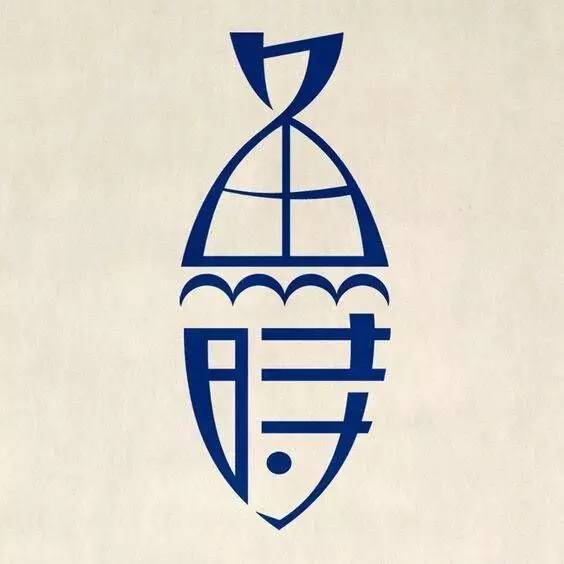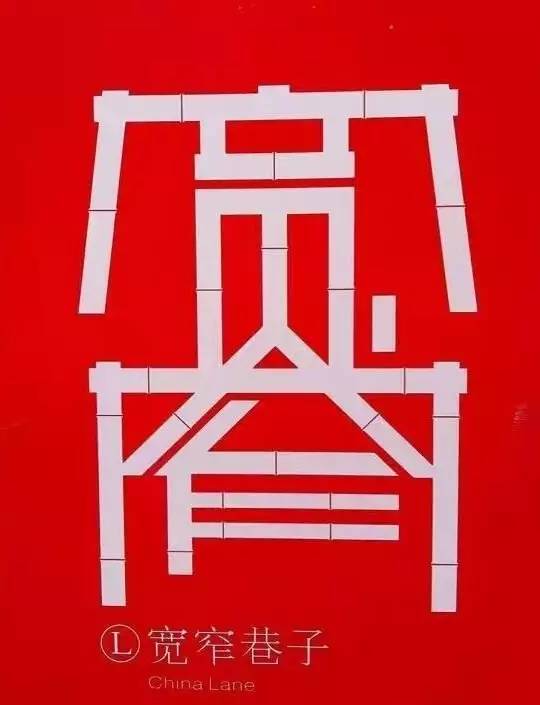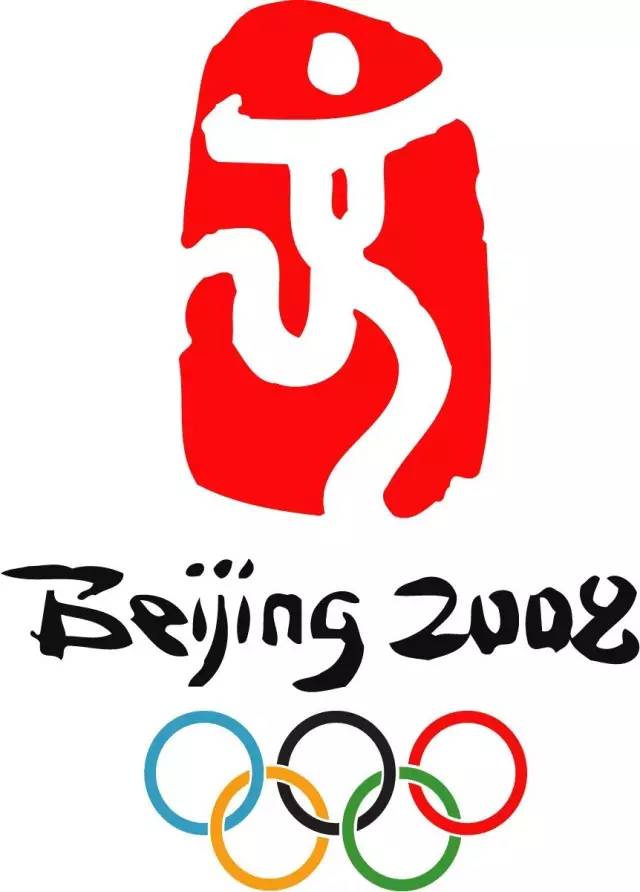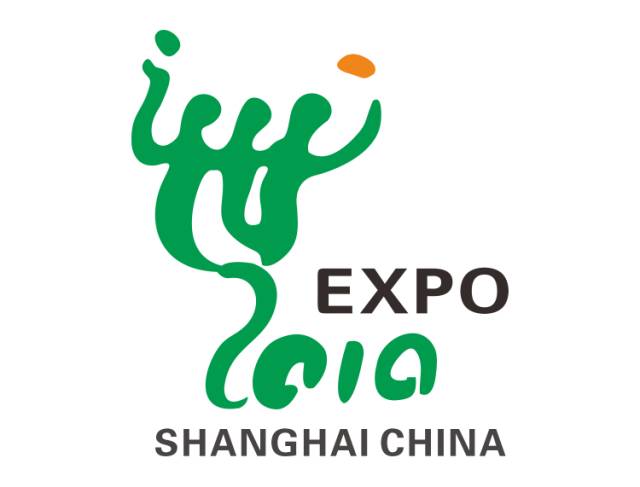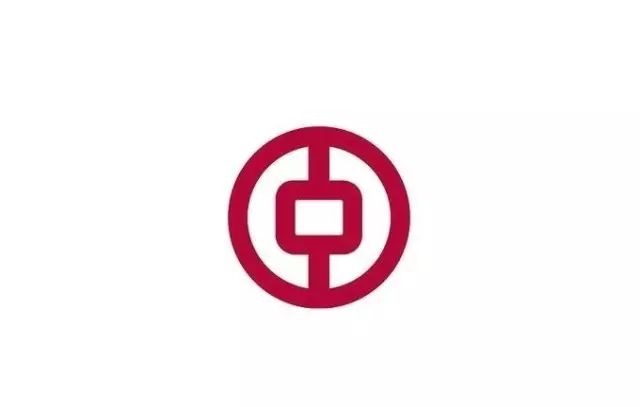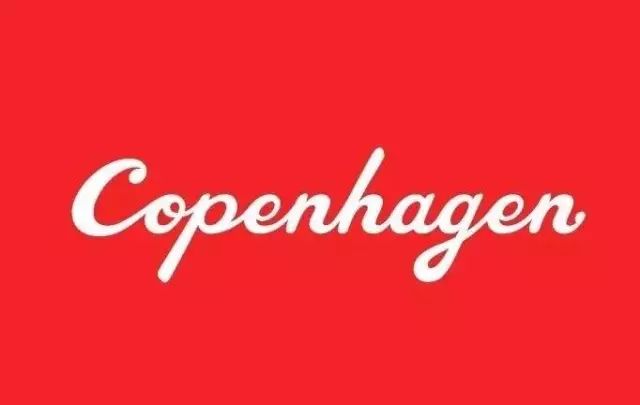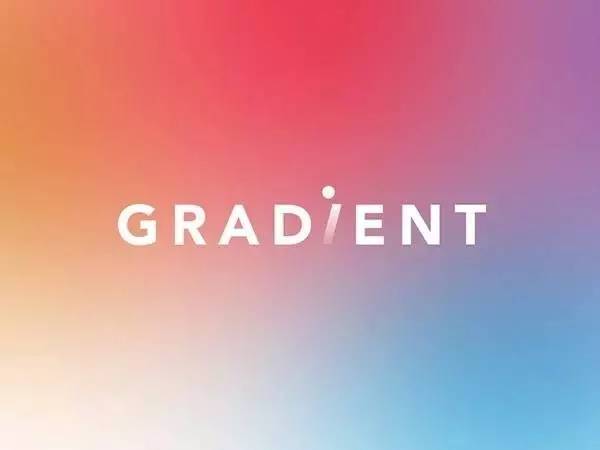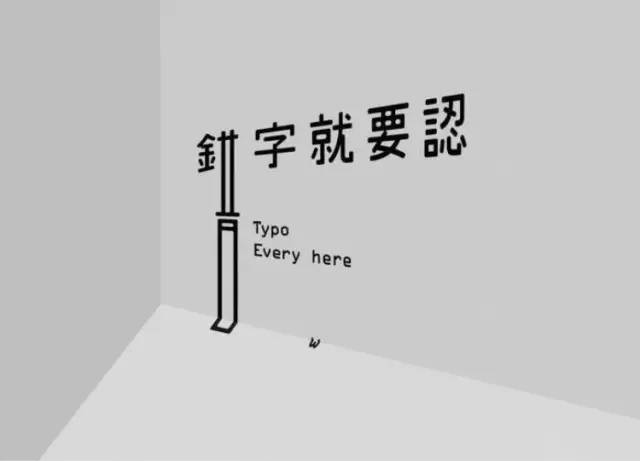
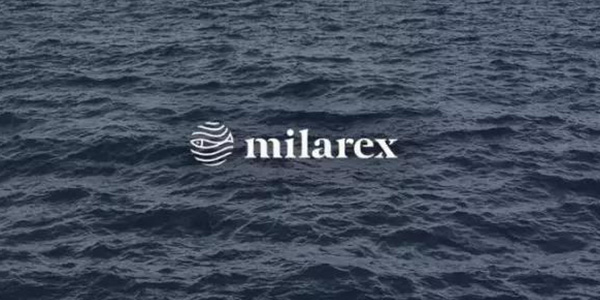
Logo字体设计的神奇效果是什么?
文字是人类沟通的重要载体。在设计领域,文字早已成为视觉传达的媒介之一。Logo字体设计以其简单、美观、概括性高等特点,受到了许多品牌的青睐。
字体设计的概念
字体设计是为了达到某种特殊的需要,经设计者深入分析品牌特点后,再融入企划者的思想情感所设计出的字体。Logo是Logotype一词的缩写,它指的是一个完整的、不可分割的,且具有造型性、统一性及识别性的字体设计。
在古希腊时期,“Logo”的含义除了“字”的意思,它还有“宇宙”的含义。从释义上即可看出,当时Logo的基本要求除了是有形的字以外,还必须具备完整性。
近些年来,Logo的定义更加广泛,不再单纯以文字作为表现形式。只要是具备固定形态和统一性的整体就都能被称为“Logo”。
在设计领域,字体是视觉传达和信息传达的重要媒介之一。如何运用好文字,充分利用其效能呢?其中,重要的是要去理解文字,才能做出最贴切的设计作品。
字体设计的重要性
字体设计随着社会的发展一同进步,它是人类文明演变的见证者。无论是具有形意功能的汉字,还是具有几何化特征的拉丁字母,它们都以简洁、独特的性质吸引着人们的眼球。
字体设计广泛地应用于各种领域当中,例如招贴设计、书籍设计、标志设计以及包装设计等等。
文字的主要功能是通过视觉向大众传达一些信息和意图,因此,准确性是文字表达的一大特点。尤其是在商品广告的设计上,一个标题或一个标志就能将商品的内涵准确无误地传达给消费者。
文字虽然看起来简单,但是在字体设计上却有着无限可能。只要从字的形态与编排上不断创新,就能给人带来不一样的视觉效果——或是端庄秀丽,或是欢快轻盈,又或是新颖独特。
在视觉传达的过程中,文字作为整体画面的要素之一,具有传达情感的功能。好的字体设计不仅关注局部,而且对结构、字形及整个设计都有全盘把握。一次巧妙的字体设计会令人感到愉快,甚至对背后的品牌产生好感。
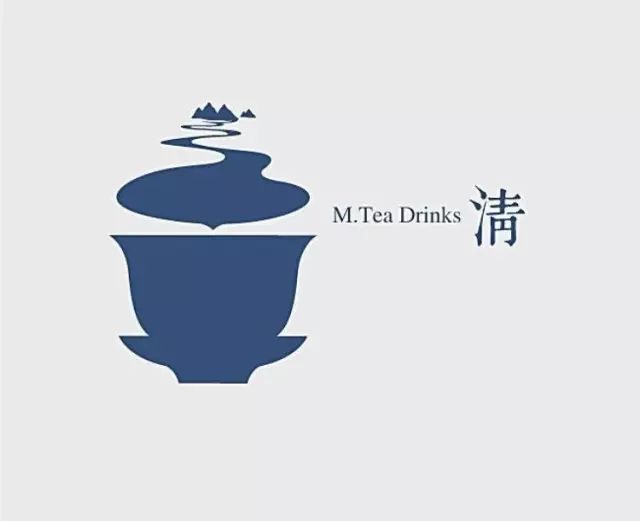
创意字体设计最大的特征是其具有装饰性。自古以来,汉字都因其独特的装饰美被用在鼎、钟、印等器物上,也被用于装饰瓷器、刺绣等工艺品。如今,创意使文字拥有了新的生命力,吸引了更多人关注的目光。
Logo字体设计对品牌的影响
Logo是联系品牌与消费者的中介之一,一个知名的品牌可以通过其知名度来扩大其标志的识别度。同样地,一个好的标志也有助于品牌获得更大的成功。
2003年4月,联想将其原有标志“LEGEND”换成“Lenovo”的主要原因是联想在准备进入海外市场的时候发现,原有的标志在多个国家已被注册。
联想为了开启自己的国际化战略,不惜花重金获得了2004年奥运会赞助商的资格,并借助这个世界性平台将自己的Logo与奥运五环连在一起,为品牌创造了更多的曝光机会。
诺基亚(NOKIA)最早是一家在芬兰Nokia小镇附近的造纸公司,它最初的标志是一条长相怪异的鱼。尽管公司早在上世纪初就进入了通信行业,但是他们依旧沿用了这个标志,直到上世纪60年代。这就导致有些人在看到这个标志时,以为这是一家有趣的饭店。
2010年10月,美国服装品牌Gap在其官网发布了新商标,一改品牌使用了20年的蓝底白字标识。不久以后,社交网络上充斥着对Gap新商标的吐槽,大量顾客宣称不会再购买此品牌商品。10月11日,Gap最终决定撤回新标,沿用之前的经典Logo。
时尚界有众多高端大气的奢侈品牌,它们作为全球时尚界的风向标,其品牌的标志也成为了独一无二的经典。例如香奈儿高雅简洁的标志、芬迪品牌的双F标志、圣罗兰富有节奏性的标志等等。
标志字体设计可谓是最富有创意的工作之一,它在方寸之间浓缩了大量的信息,通过文字表达出了不同企业的文化及风格。正如美国广告专家约翰·菲利普·琼斯所说:“品牌由品牌标志的发展而来”。
汉字在Logo设计中的运用
汉字以其独有的民族性成为了中国的标志之一。汉字字体的多样性大大地丰富了标志设计的表现形式,为设计师开拓了更为广阔的创意空间。
在中国古代,汉字早已作为设计元素出现过。它从最原始的基本形状,发展到当今富有创意且含义深刻的标志符号。目前汉字标志设计的应用在我国很普遍,也十分具有代表性。
2008年,北京奥运会的会徽采用了汉字中的“京”字,完美地将中国传统文化元素与运动的人物形象相结合,形象地表现出了富有中国特色的奥运精神及人文情怀。2010年,上海世博会标志以“世”字为主体架构,采用了中国书法率性的表现手段,巧妙地将传统文字与时尚理念相结合,成为了汉字标志设计的典范之一。
由于汉字自身具有形式美感,因此在许多标志设计中都有借汉字的外形表达含义的案例。例如中国银行的标志借用古代铜钱的造型特征,将外部形状与汉字“中”相连接,造型简练、含义突出;上海永久牌自行车的标志利用“永久”二字,组合成了一个自行车的造型。
中国银行Logo
以汉字作为标志的最大特点,就是以最简洁的方式把事情表达得简单易懂,让人看过标志以后就能理解其中的含义。
Logo字体设计的发展趋势
如今,我们可以利用电脑和数字技术使所有形式的字体都成为可能。经济的发展和品牌之间激烈的竞争推动了新的字体样式不断诞生,字体设计正向着多元化的方向发展。
简洁是现代标志字体设计的主流风格。无论是字体设计还是字体排列,现在的设计者都偏爱使用极简风格的造型,使Logo更加突出。
图形化是文字起源时的状态,由象形发展到象意是一个漫长的进化过程。现在许多Logo中的字体都图形化到了极致,这使字体的信息承载功能变得更加强大。
无论是中国的传统艺术还是西方的涂鸦,都足以证明很多设计师在思考字体的设计过程中费了很多心思。在现代标志字体设计中,装饰字体已有了更广泛的含义,它可以通过多元化的装饰手法来表达,例如材质、油漆、灯饰、马赛克褶皱带等等。
当下,字体可以绘制成三维的视觉效果,如平视、投影等多种效果的立体字。这种效果被广泛运用到网页的Logo设计上,它具有对比鲜明、视觉冲击力强等特点。
材质字体是一种利用各种材料的肌理效果,实现字体创意的设计手法,有缠绕、拼贴、排列组合等视觉字体技术。有些材质字体是由计算机制作而成的,有些材质字体则是将摄影收集的素材转化成图形材料。
设计是一种国际化的语言,它不但有利于文化的交流,也使各个民族的特色有了展示的平台。随着经济的发展和科技的进步,字体设计的表达形式及传播途径将会有更高层次的发展,给人们带来无限惊喜。